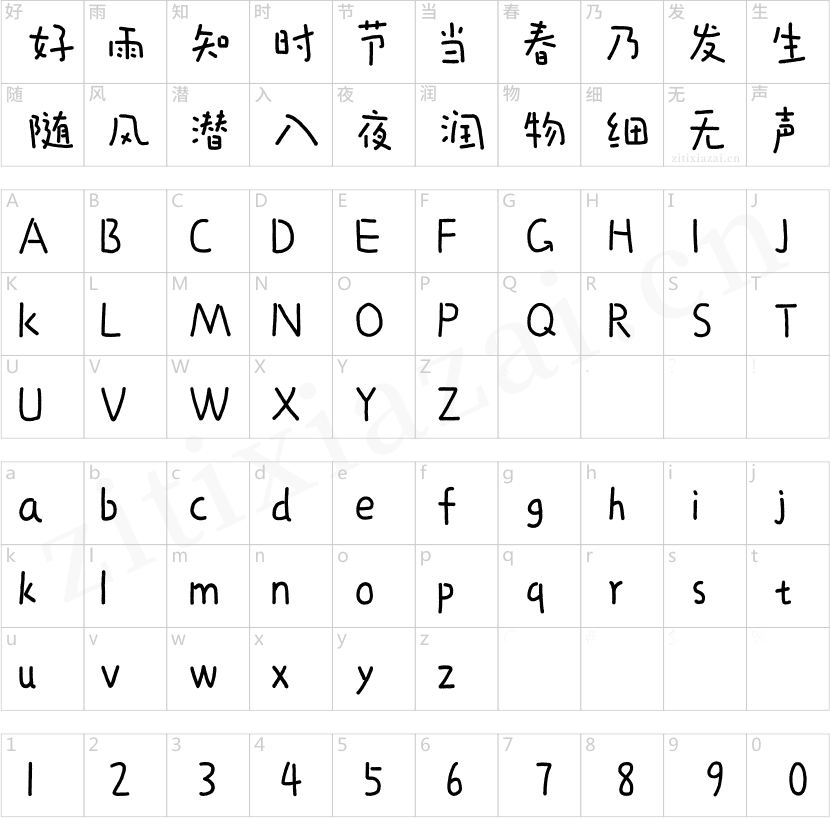
龚帆悦心体粗
龚帆悦心体粗,这款字体结构工整、笔画清晰,兼顾美观与易读性,适用于标题、正文、海报、包装、LOGO 等多种场景。字形优雅稳定,风格百搭耐看,适配日常排版与创意设计,让文字呈现更舒适、更具质感。龚帆悦心体粗一笔一画,皆是细节,以均衡的比例、流畅的线条打造舒适视觉体验,字形端正大气,风格简约现代。无论是商业设计、品牌宣传还是日常排版,都能轻松驾驭,让文字更有格调与力量。龚帆悦心体粗字体下载。
字体设计既能很好的展示汉字的魅力,又能传递特殊的情感,所以每一个字都是匠心的打造,除了要考虑把字的性格表达出来之外,还要考虑每一个字笔画的造型,笔画的气质,结构的摆放,考虑如何把传统字与设计做一个结合,在识别性和艺术性之间寻找一个平衡点,最后诠释出一个独一无二的原创字体。